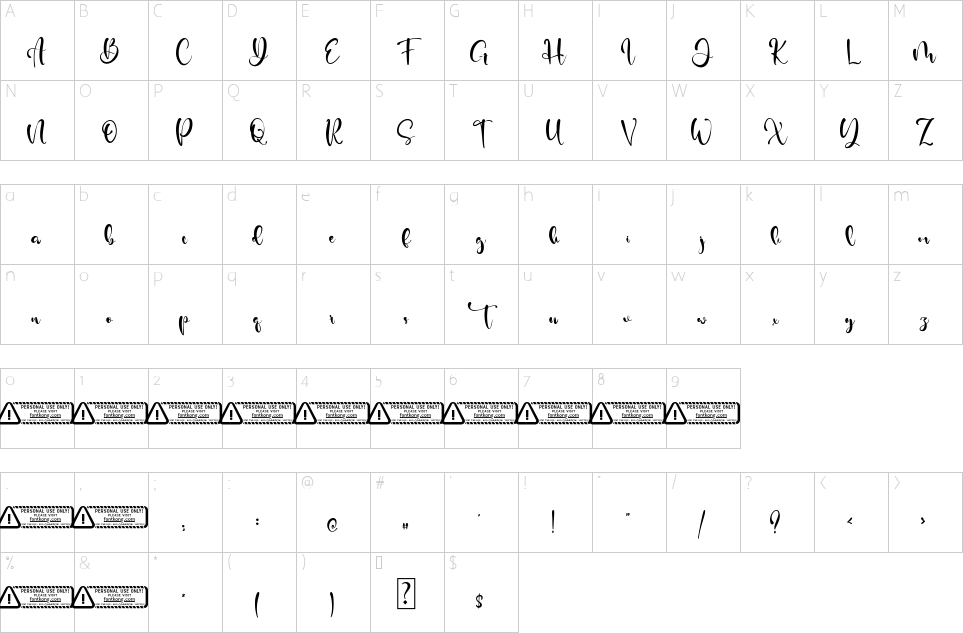
A Diana David Font é uma elegante opção para designers gráficos que valorizam a sofisticação minimalista em suas criações. Desenhada pelo desconhecido designer Font Kong, esta fonte vem em versões compatíveis com Windows e Mac, facilitando seu uso tanto no trabalho de desktop quanto nas plataformas móveis. Com um design moderno e fácil de ler, Diana David oferece uma solução perfeita para projetos que exigem um estilo minimalista e sofisticado. Com apenas 1,230 downloads em sua disponibilidade inicial, a Diana David pode ser uma escolha interessante tanto para profissionais iniciantes quanto para designers mais experientes procurando um novo recurso para incorporar em seus trabalhos.